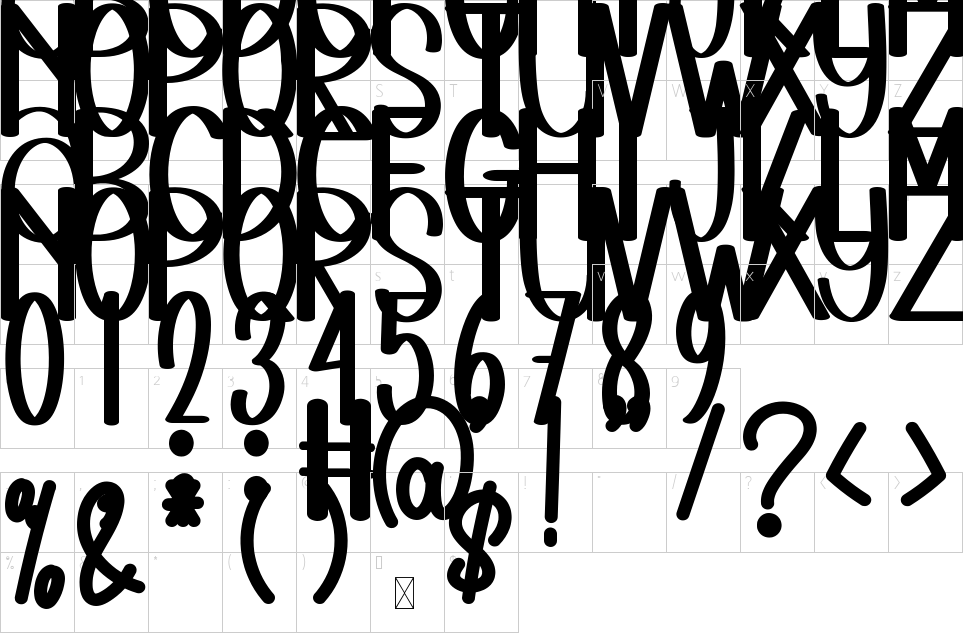
A fonte Santa Coffee oferece um toque descontraído e aconchegante, perfeita para aqueles que buscam uma fonte que combine charme e simplicidade em seu design. Inspirada na atmosfera de um bom café da manhã em família, Santa Coffee traz uma dose generosa de conforto e bom gosto. Desenvolvida pela InermediaSTUDIO, essa fonte gratuita é um charme para qualquer projeto que valorize a informalidade e a harmonia. Com uma interface fácil de usar, ela se destaca como uma opção versátil para aplicações gráficas, texturas e design de logotipo. Com apenas uma rápida instalação, a Santa Coffee vai transformar qualquer projeto em um verdadeiro delicioso café da manhã digital. Não há como resistir a ela, uma vez que já foi baixada 388 vezes.